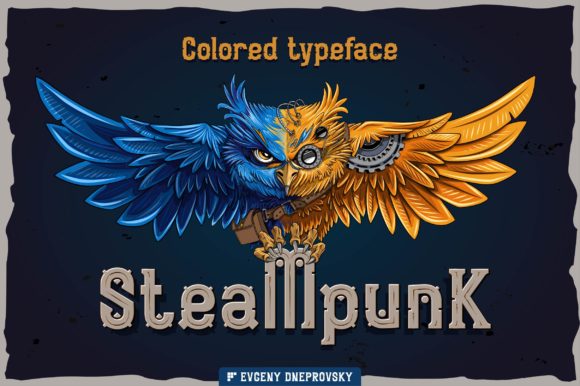
Creativefabrica Steampunk Font
[Creativefabrica] Steampunk Font
Стемпанк - это невероятно уникальный цветной шрифт.
Мастерски разработанный, чтобы стать настоящим фаворитом, этот шрифт способен поднять каждую вашу творческую идею на самый высокий уровень!